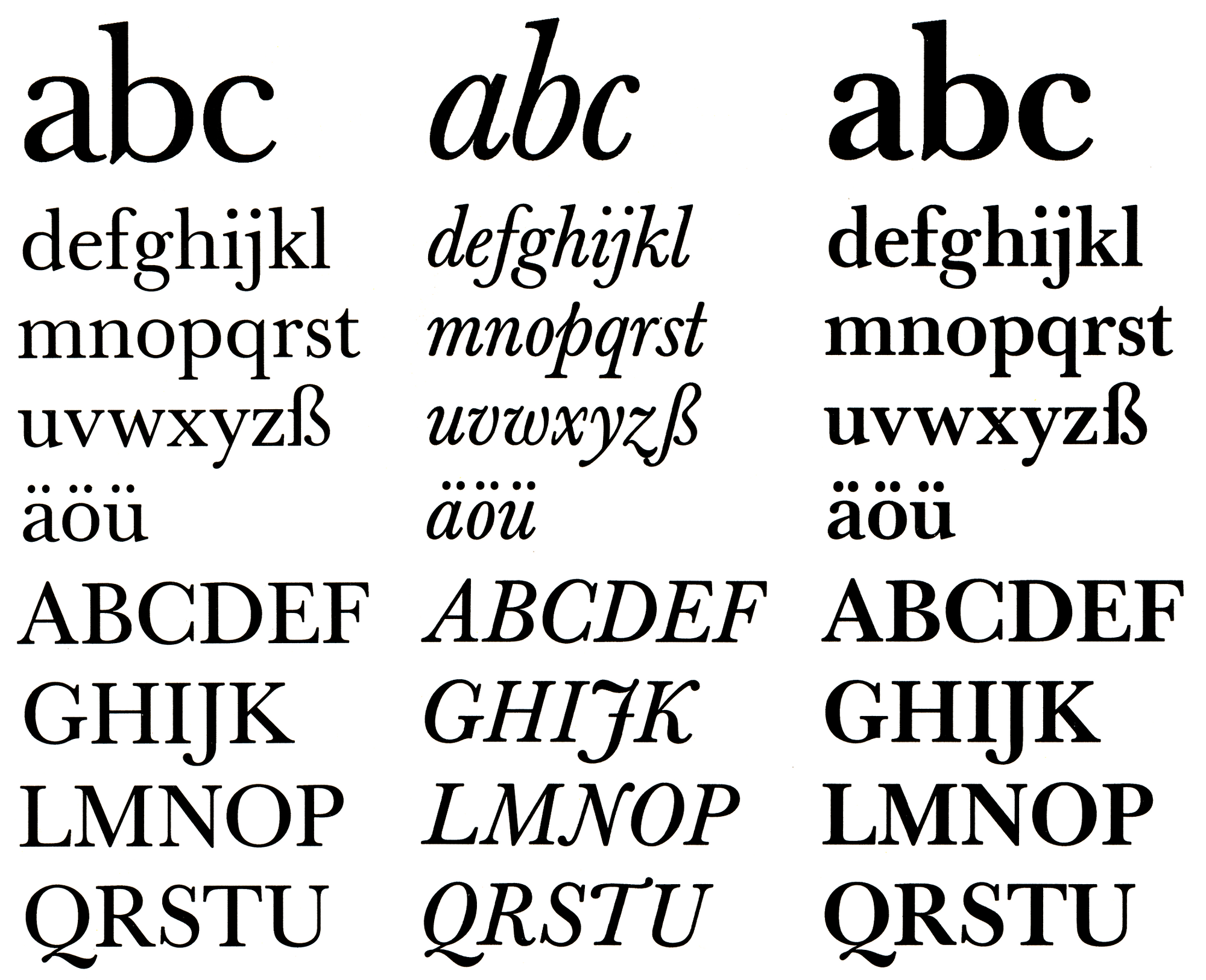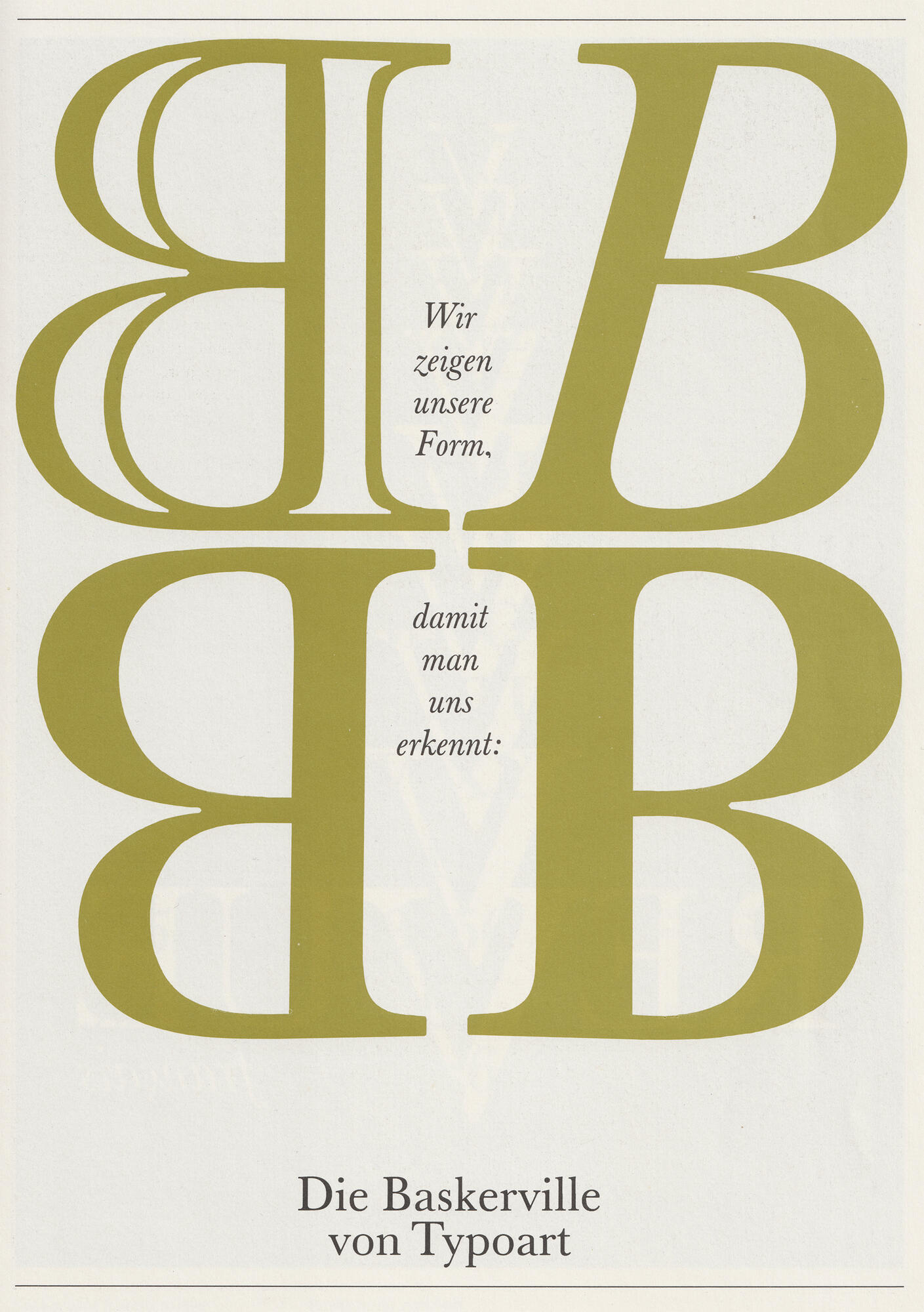
Font-Wiki: Typoart-Baskerville
Die Typoart-Baskerville ist eine Neubearbeitung der Schriften von John Baskerville für den Fotosatz durch Volker Küster und Hans-Peter Greinke.
Eine Digitalisierung auf Basis der Originalmaterialen wurde über Elsner+Flake in zwei optischen Größen und drei (TB) bzw. vier Schnitten (TH) verfügbar gemacht. Der zusätzliche Schnitt in den Schaugrößen ist eine lichte Version.
Fotosatz-Muster